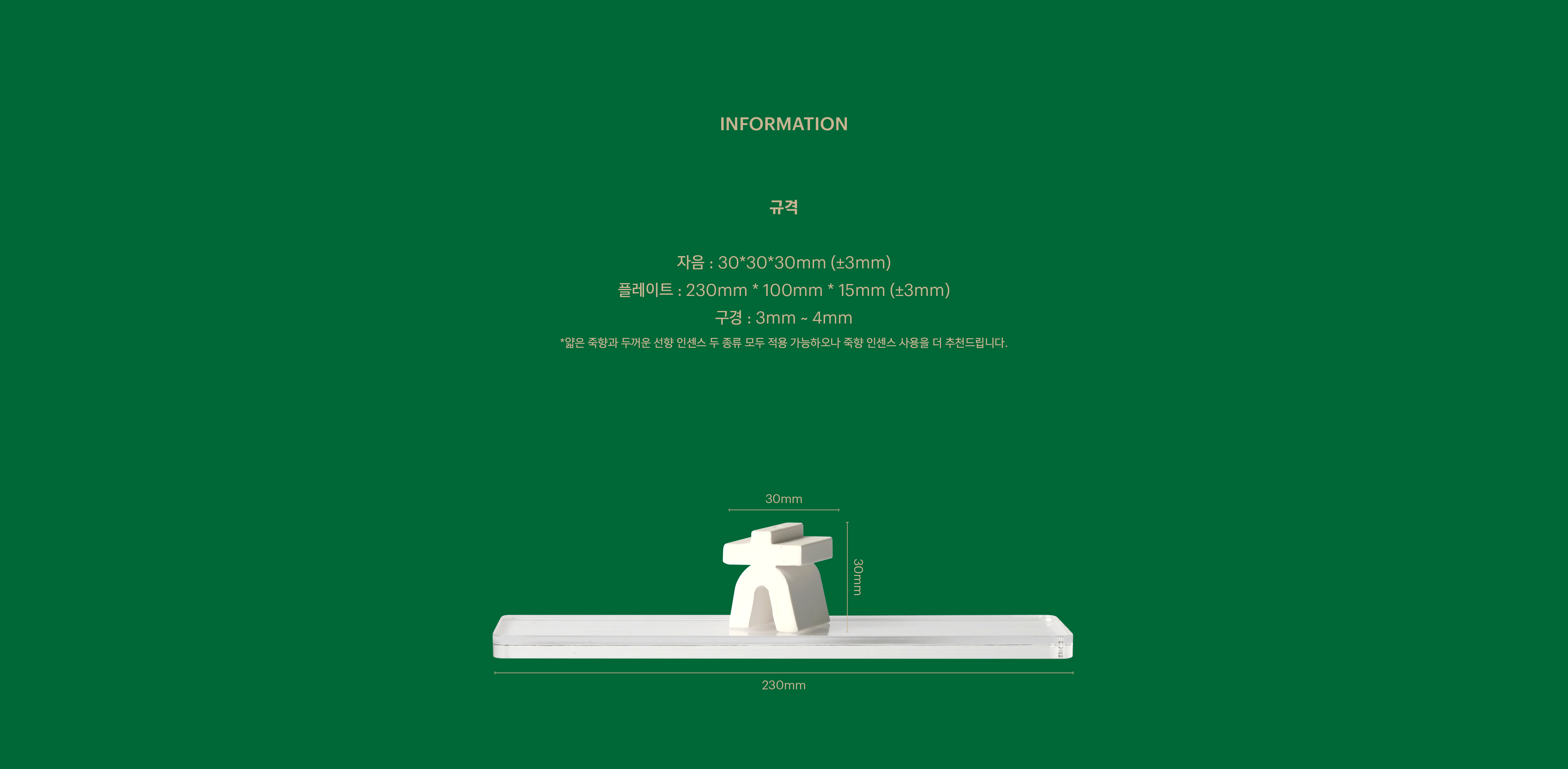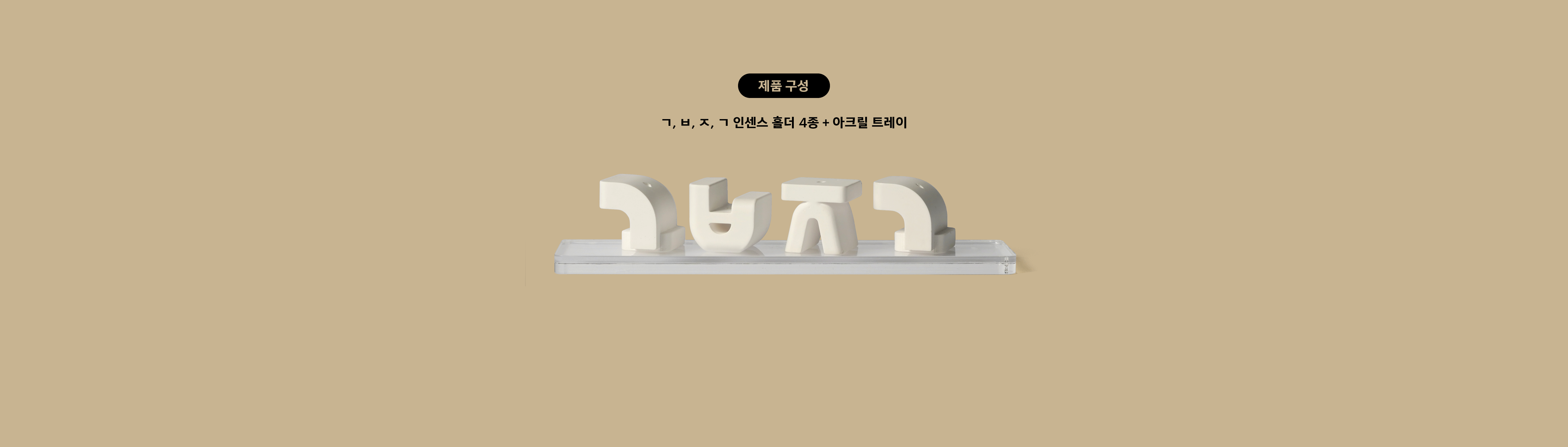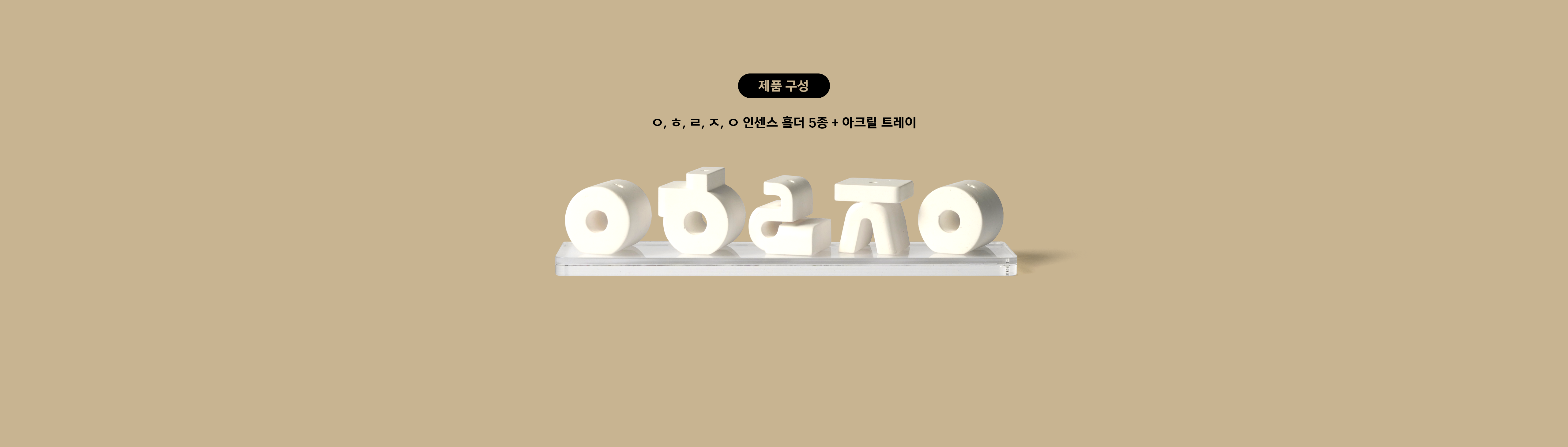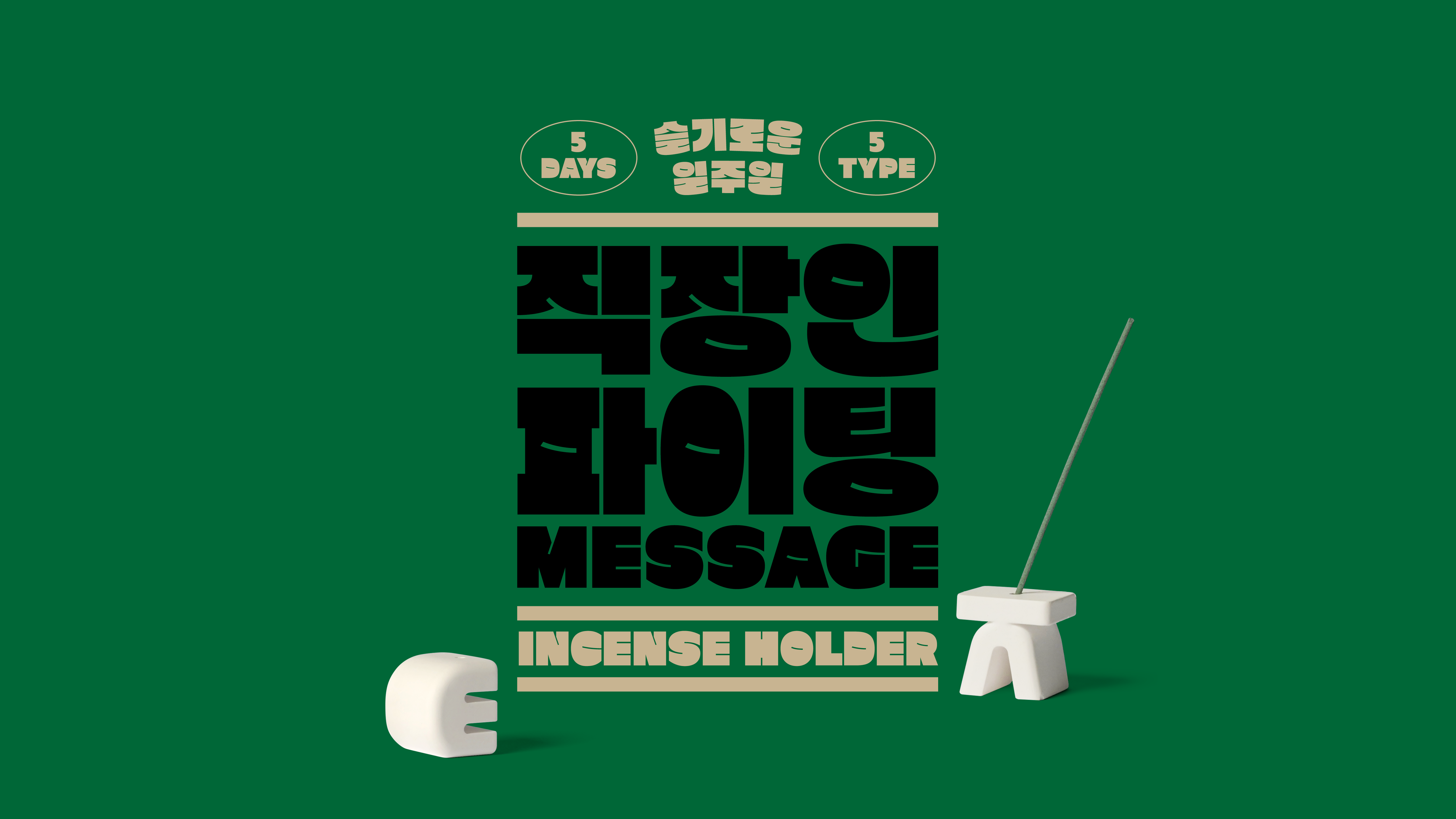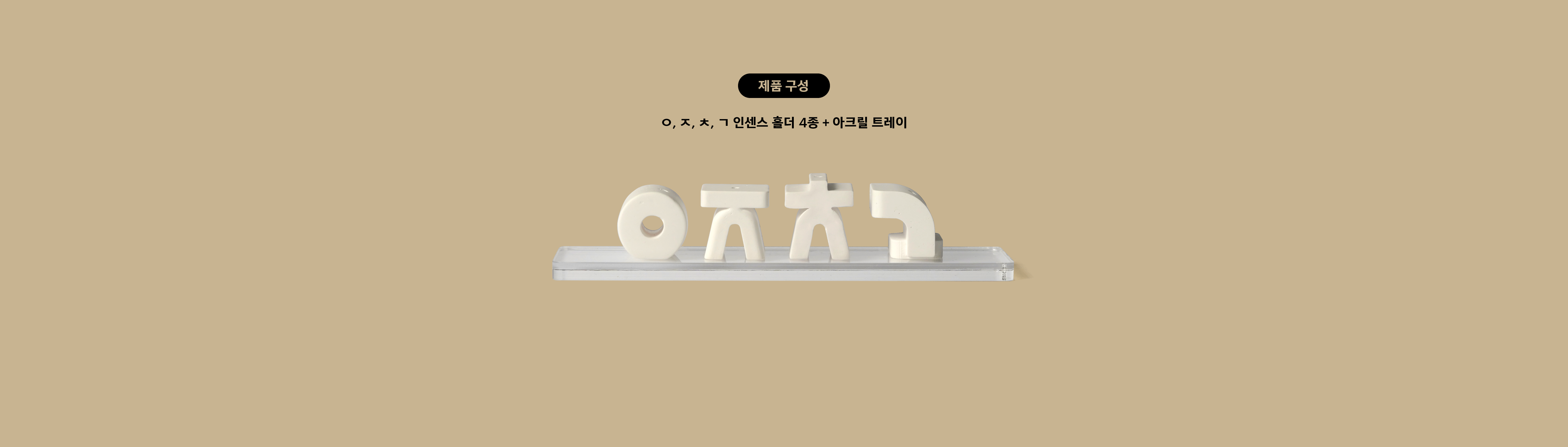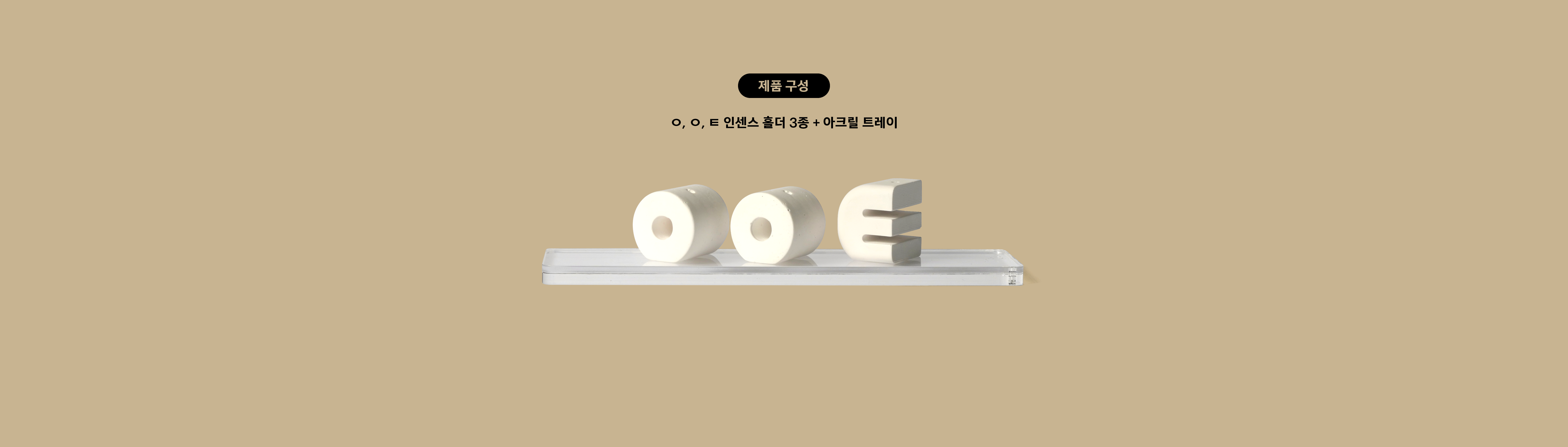
채롱 인센스 홀더
채롱
채롱은 한글 자음을 활용해 새하얀 인센스 홀더를 빚어내는 브랜드입니다.
누구나 내 삶의 풍경에 좋아하는 향과 메시지를 배치하기를 바라는 마음으로
한글 인센스 홀더를 제작하고 있어요.
폰코와 채롱은 새해부터 출근하기 싫은 직장인들을 위로하기 위해
직장인 파이팅 메시지를 테마로 한글 인센스 홀더를 조합해보았습니다.
월요팅, 오히려 좋아, 오저치고(오늘 저녁 치킨 고), 토닥토닥, 가보자고!
깨알 같은 문구로 구성한 채롱의 한글 인센스 홀더와 함께,
열일하는 나를 응원해주자고요!
채롱은 한국 전통문화가 생활에 스며들 수 있도록, 전통문화를 품은
인테리어 소품을 만드는 브랜드입니다. 오색 빛깔 바구니라는 뜻의 단어에,
빛나는 것들로 공간을 채우고 싶은 마음을 가득 담았습니다. 채롱이 선보이는
첫 번째 제품은 한글 형태로 빚은 인센스 홀더입니다. 많은 분들이 자신만의 공간에
좋아하는 메시지를 배치하고, 좋아하는 향기를 채워넣으며 충만한 기분을
느껴보셨으면 좋겠습니다.